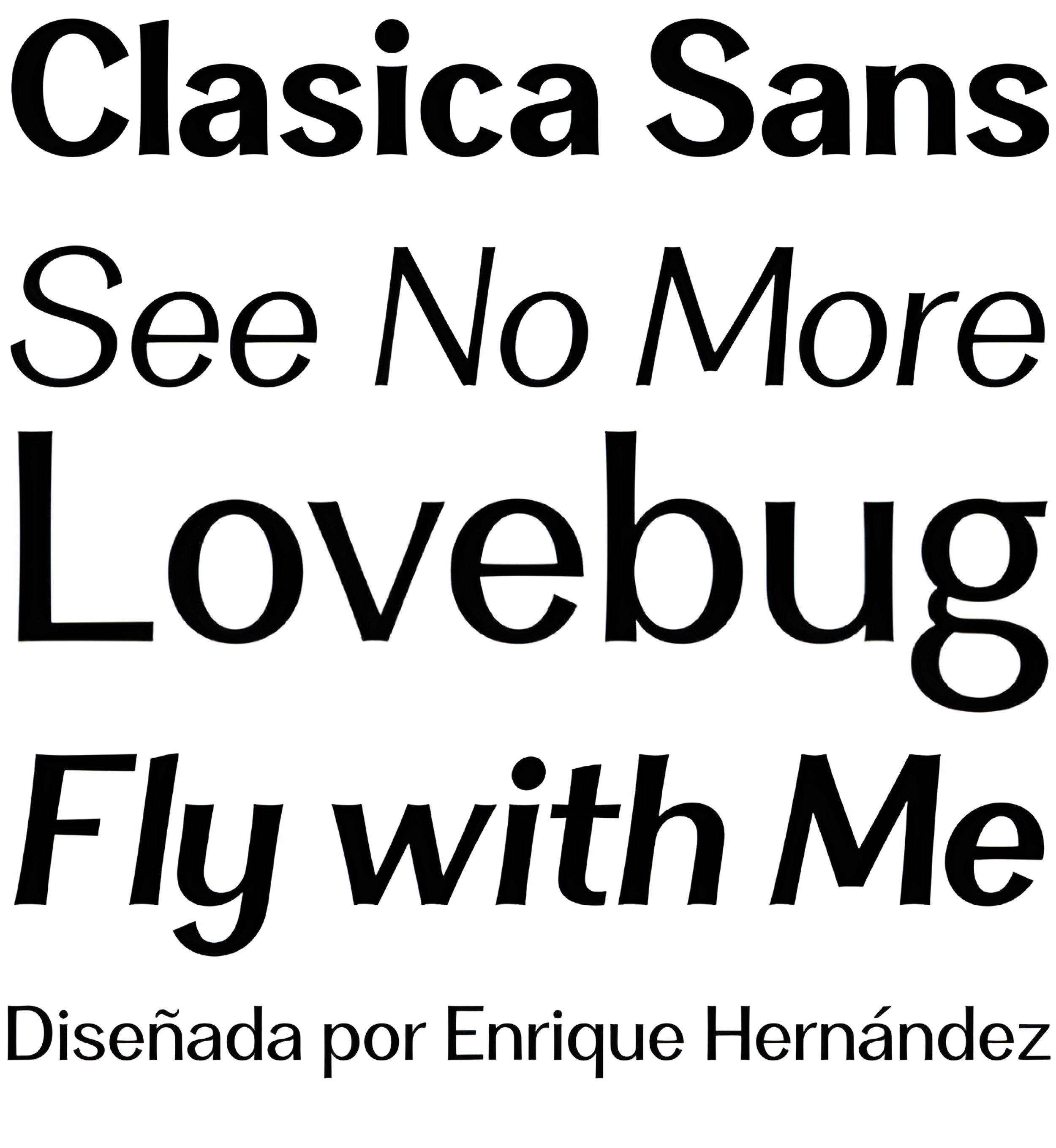
| Año | 2015 |
| Créditos | Enrique Hernández |
| Descripción | Clasica Sans es un tipo de letra fresco y contemporáneo, compuesto por 7 fuentes estándar más cursiva. Es perfecta para publicaciones y diseño impreso. Clasica Sans se presenta en varios pesos, que se adaptan bien a párrafos con tamaños de texto pequeños y grandes. Independientemente de su uso, tamaño o alineación, la familia mantiene un aspecto sólido, gracias a su contraste equilibrado. En resumen, es una fuente basada en proporciones clásicas, pero con un aspecto fresco y contemporáneo, ideal para los diseños más versátiles. |